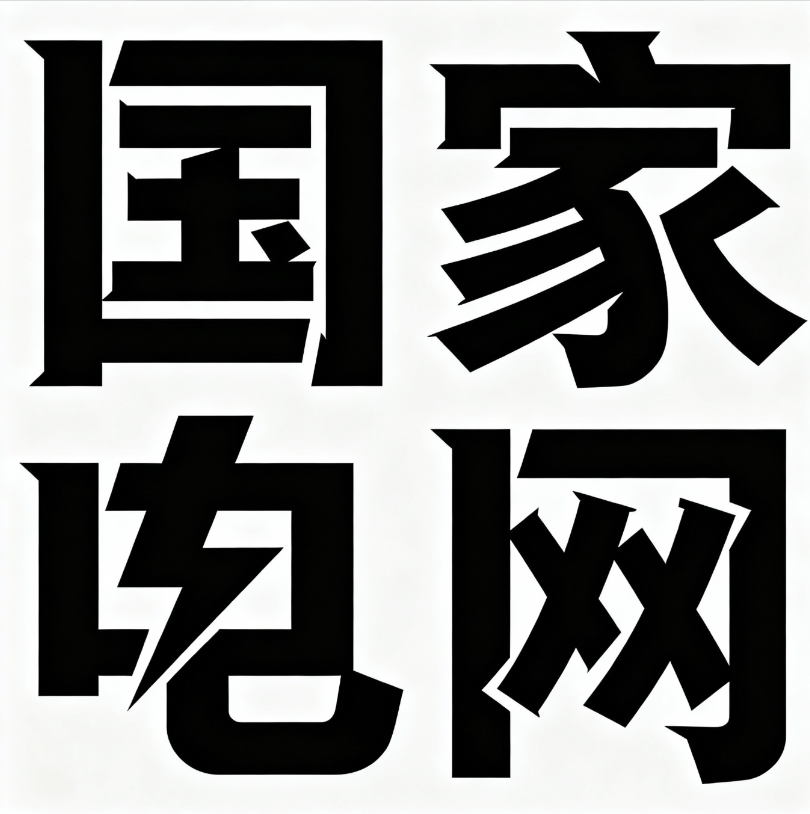
白底黑字,字体设计,字体居中,上下留白,战斗...
白底黑字,字体设计,字体居中,上下留白,战斗...AI字体提示词
风格定位
适合做风格探索与字形灵感延展。
适合场景
海报设计、品牌标题、电商设计、创意视觉
白底黑字,字体设计,字体居中,上下留白,战斗主题艺术字体 “国家电网”,激进解构笔画,融入闪电箭头元素,不规则自由排版,极端厚重切割笔画,传递激烈对抗与能量爆发氛围,适配赛事、活动宣传设计 。极简留白空间。